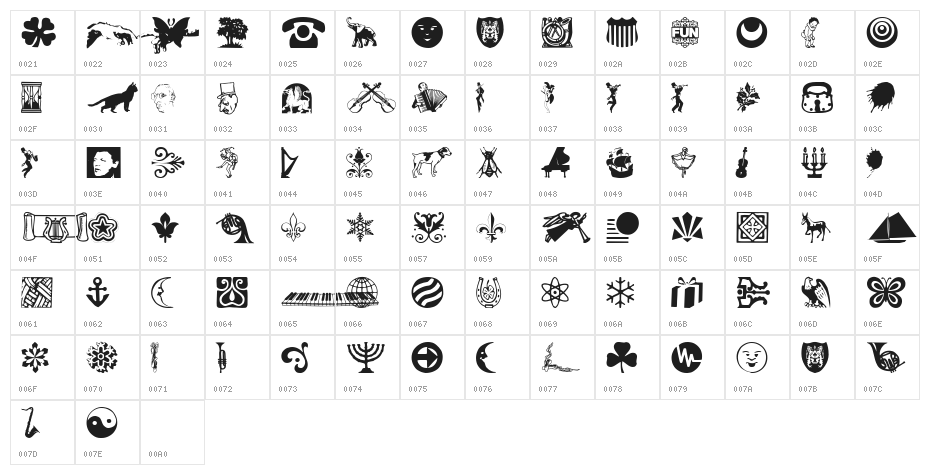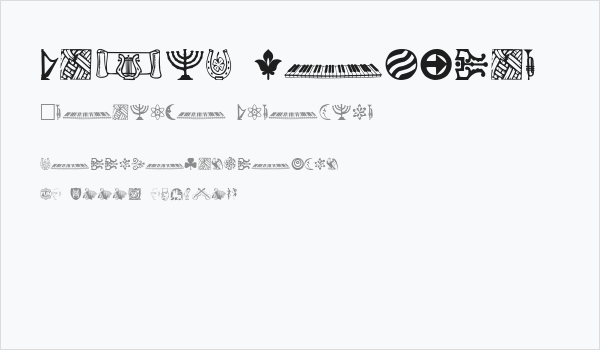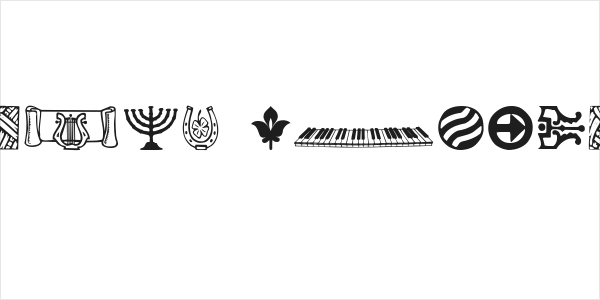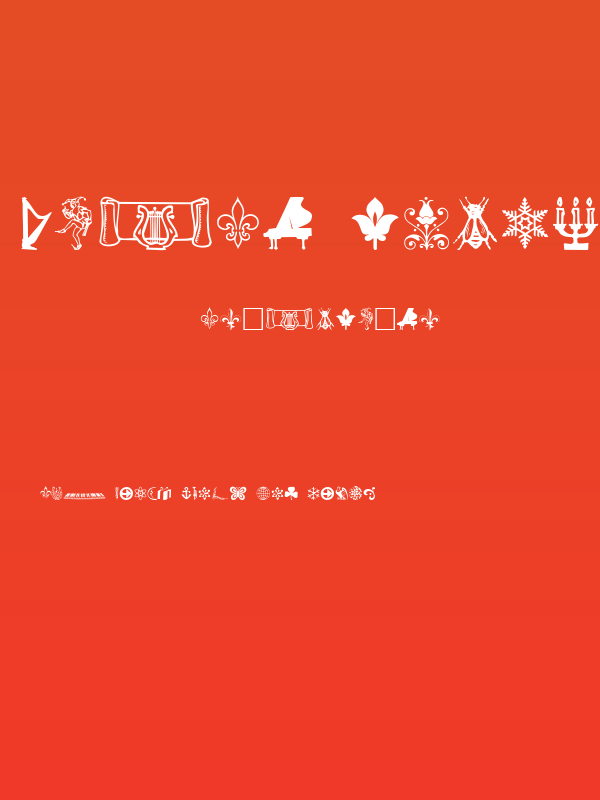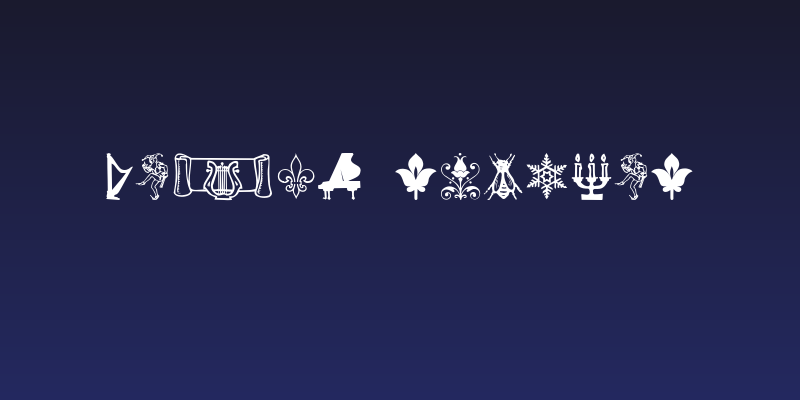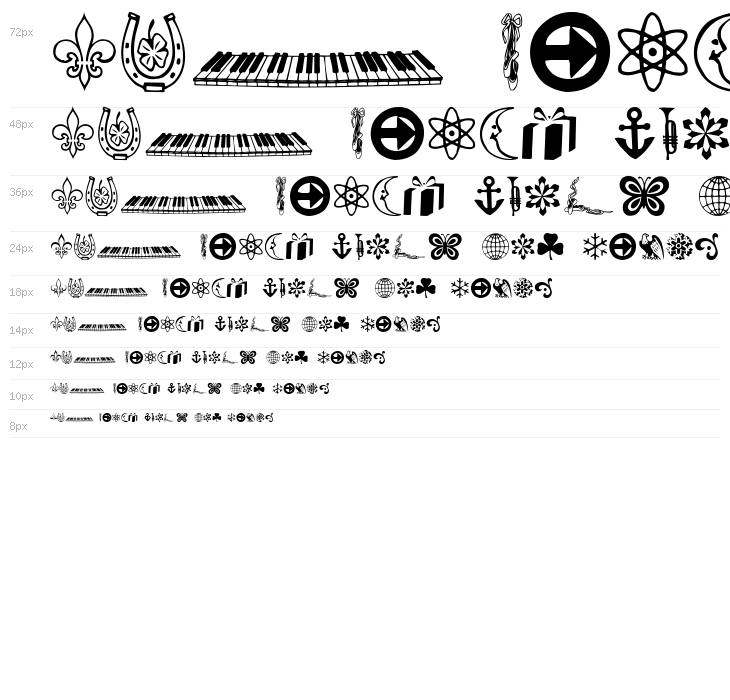
DaOth Regular Font
| Stile generale | Decorative, Whimsical, Vintage |
| Caso d'uso | Icons, Decorative elements, Themed graphics |
| Progetti proposti | Invitations, posters, scrapbooking, themed event materials, educational worksheets, decorative borders, and playful branding. |